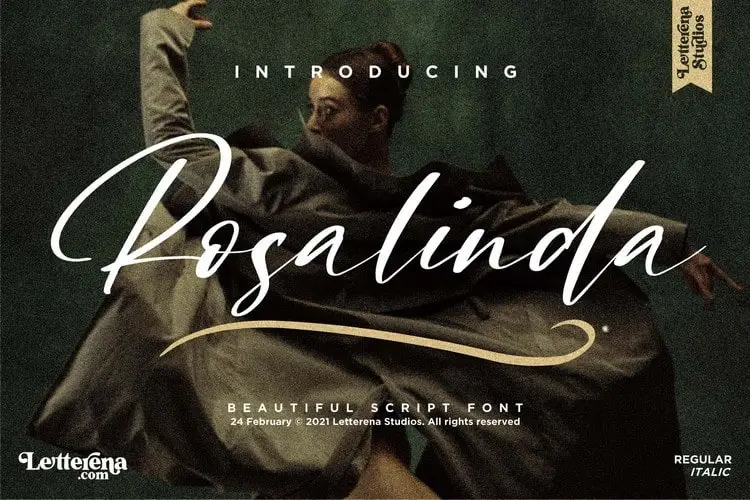
A Rosalinda Calligraphy Font é uma tipografia de escrita elegante criada pela Letterena Studios para projetos diversos que valorizam a estética delicada e sofisticada do script. Esta fonte, simples e sofisticada, está perfeitamente adaptada para criações como logotipos, trabalhos de marca, designs de móveis de casa, embalagens de produtos, chinelos, cartões de citação, convites, presentes de aniversário, etiquetas, fotografia e até mesmo marcas especiais. A Rosalinda é uma fonte perfeita para quem busca dar um toque único e delicado a projetos variados. Seja você designer gráfico ou hobbyista que se dedica à criação digital, essa fonte é um recurso imprescindível para tornar suas ideias ainda mais memoráveis.